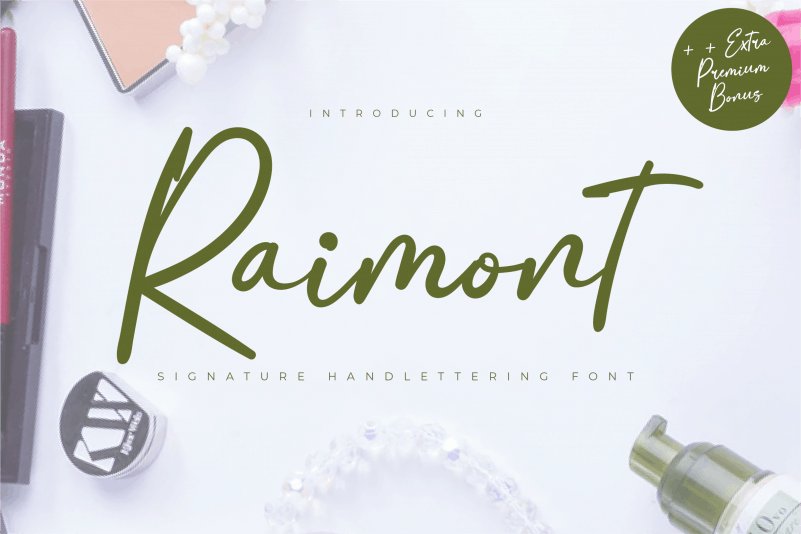
Raimont Script Font é uma fonte elegante criada à mão, que transmite sofisticação através do estilo tradicional da calligrafia. Este ícone do design moderno mantém seus traços únicos e sua influência de escrita alegre, tornando-o perfeito para qualquer projeto visual. A cada caractere é um momento único, repleto de harmonia e criatividade que pode transformar seu trabalho em algo extraordinário. Raimont Script Font é uma escolha inteligente para designers buscando um toque especial ao criar ambientes digitais atraentes. Faça sua marca realmente chamativa com este design versátil e poderoso, capaz de atingir o público de uma maneira única. Ele está disponível na categoria de fontes de escrita, cuidadosamente criado pelo designer twinletter, que oferece um rico conjunto de características para personalizar conforme seu gosto pessoal.